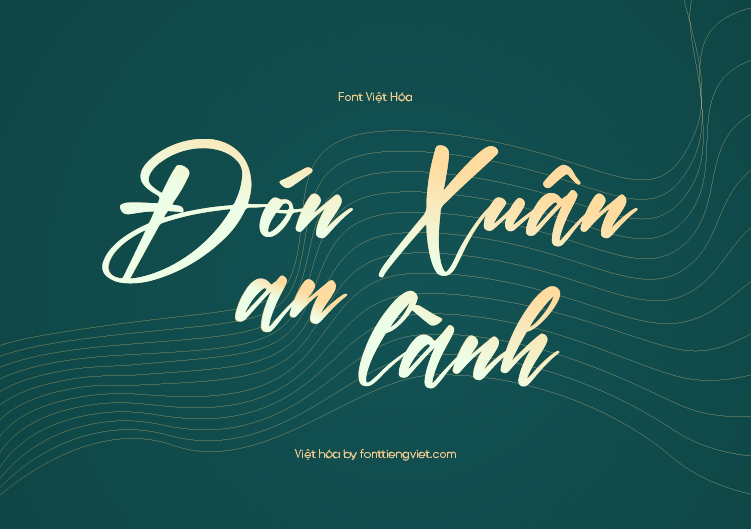
Font Việt hóa 1FTV VIP Dita & Rusta – Tết
Font Việt hóa 1FTV VIP Dita & Rusta – Tết: Bộ đôi hoàn hảo cho thiết kế Tết 2026
Trong không khí rộn ràng của những ngày giáp Tết, việc tìm kiếm một bộ Font Miễn Phí chất lượng để thiết kế bao bì, thiệp chúc mừng hay banner quảng cáo là ưu tiên hàng đầu của các designer. Bộ Font Việt hóa 1FTV VIP Dita & Rusta – Tết chính là giải pháp tuyệt vời mang đến sự kết hợp giữa nét hiện đại và truyền thống. Với sự chăm chút tỉ mỉ trong từng đường nét, bộ font này không chỉ giúp nội dung trở nên nổi bật mà còn truyền tải trọn vẹn tinh thần lễ hội của người Việt. Đây là lựa chọn lý tưởng cho các dự án sáng tạo cần sự độc đáo, sang trọng và đầy tính nghệ thuật trong dịp đầu xuân năm mới.
Khám phá đặc điểm nổi bật của Font Việt hóa 1FTV VIP Dita & Rusta – Tết
Sự kết hợp tinh tế giữa phong cách Dita và Rusta
Bộ Font Việt hóa 1FTV VIP Dita & Rusta – Tết là sự giao thoa độc đáo giữa hai phong cách thiết kế đối lập nhưng vô cùng hài hòa. Trong khi Dita mang đến vẻ đẹp thanh mảnh, sang trọng với các đường nét uốn lượn mềm mại, thì Rusta lại tạo điểm nhấn bởi sự mạnh mẽ, vững chãi và mộc mạc. Sự kết hợp này cho phép người dùng linh hoạt trong việc phối hợp tiêu đề và nội dung, tạo nên một bố cục thiết kế có chiều sâu. Đặc biệt, phiên bản Việt hóa này đã được tối ưu hoàn toàn các dấu câu tiếng Việt, đảm bảo không xảy ra lỗi hiển thị khi đánh máy, giúp quy trình thiết kế trở nên mượt mà và chuyên nghiệp hơn bao giờ hết.
Tính ứng dụng cao trong trang trí và quảng cáo Tết
Sức hút của Font Việt hóa 1FTV VIP Dita & Rusta – Tết nằm ở khả năng biến hóa đa dạng. Bạn có thể sử dụng bộ font này để thiết kế các phong bao lì xì may mắn, các bảng hiệu chúc mừng năm mới tại trường học hoặc công sở. Nhờ vào định dạng ttf và otf phổ biến, font chữ tương thích tốt với các phần mềm đồ họa chuyên nghiệp như Adobe Photoshop, Illustrator hay cả những ứng dụng thiết kế đơn giản trên điện thoại như Canva. Với những nét chữ được cách điệu theo hướng thư pháp hiện đại, bộ font giúp các thông điệp chúc Tết trở nên ấm áp và gần gũi, tạo ấn tượng mạnh mẽ với người xem ngay từ cái nhìn đầu tiên.
Hướng dẫn sử dụng Font Việt hóa 1FTV VIP Dita & Rusta – Tết hiệu quả
Mẹo phối màu và bố cục cho thiết kế xuân
Để phát huy tối đa vẻ đẹp của Font Việt hóa 1FTV VIP Dita & Rusta – Tết, bạn nên ưu tiên sử dụng các gam màu truyền thống như đỏ, vàng kim hoặc xanh lá cây đậm. Khi thiết kế banner, hãy dùng phong cách Rusta cho các từ khóa chính như “Chúc Mừng Năm Mới” để tạo sự cứng cáp, và dùng Dita cho các câu đối hoặc lời chúc nhỏ bên dưới để tăng phần duyên dáng. Việc điều chỉnh khoảng cách chữ (kerning) cũng rất quan trọng để đảm bảo tính dễ đọc trên các nền hoa văn rực rỡ của ngày Tết. Hãy thử thêm các hiệu ứng đổ bóng nhẹ hoặc viền vàng để chữ nổi bật hơn trên nền đỏ thắm.
Lợi ích khi sử dụng font chữ đã được Việt hóa chuẩn
Sử dụng bộ font này giúp bạn tiết kiệm đáng kể thời gian so với việc phải tự chỉnh sửa dấu cho các font quốc tế. Font Việt hóa 1FTV VIP Dita & Rusta – Tết được thiết kế dựa trên tiêu chuẩn hiển thị sắc nét, không bị nhòe khi in ấn khổ lớn. Điều này đặc biệt quan trọng đối với các nhà in ấn và các bạn học sinh, sinh viên đang thực hiện các dự án trang trí báo tường hay tập san chào xuân. Sự đồng bộ về kiểu dáng giữa các ký tự có dấu và không dấu tạo nên một tổng thể chuyên nghiệp, nâng tầm giá trị cho mọi sản phẩm thiết kế mà bạn tâm huyết thực hiện.
Kết luận về bộ Font Việt hóa 1FTV VIP Dita & Rusta – Tết
Tổng kết lại, bộ Font Việt hóa 1FTV VIP Dita & Rusta – Tết là một tài nguyên quý giá không thể thiếu trong kho công cụ của bất kỳ ai yêu thích thiết kế đồ họa. Với khả năng tương thích cao, nét chữ đẹp mắt và ý nghĩa phong thủy tốt lành, bộ font này sẽ góp phần mang lại sự thành công cho các dự án truyền thông dịp Tết 2026. Hãy nhanh tay cập nhật thêm các bộ Font Miễn Phí, Font Việt Hóa, Font Việt hóa 1FTV VIP Dita & Rusta – Tết để làm phong phú hơn phong cách cá nhân của mình. Hy vọng rằng những chia sẻ trên sẽ giúp bạn có thêm nguồn cảm hứng sáng tạo để tạo ra những tác phẩm đậm chất xuân, mang niềm vui và tài lộc đến với mọi người thông qua từng con chữ.